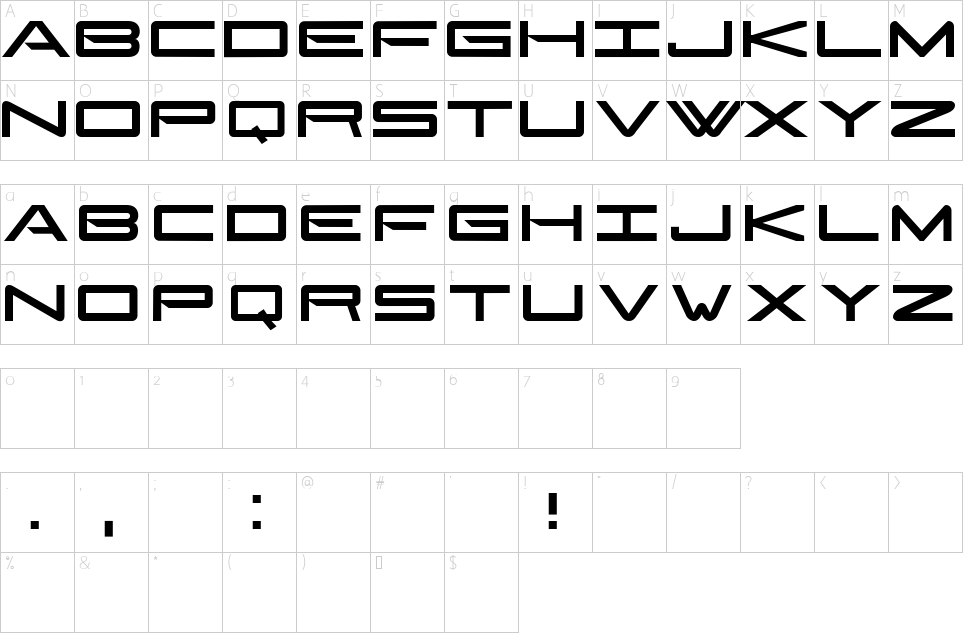
Aqui está uma descrição em português do Brasil para a página de download da font ‘Gonzales Sans Font – 1001 Free Fonts’: Descubra Gonzales Sans, uma elegante e moderna fonte sans-serif disponível gratuitamente para Windows e Mac. Desenhada por Manfred Klein, esta fonte é perfeita para projetos que exijam sofisticação e simplicidade no design. Com um estilo minimalista mas versátil, Gonzales Sans combina perfeitamente com vários estilos de design gráfico, incluindo branding, interfaces de usuário modernas e materiais digitais. Sujeite-se ao bom olhar da comunidade de designers que já usaram esta fonte em suas criações. Se você está procurando por uma opção prática para personalizar seu website ou aplicativo sem precisar gastar nada extra na sua conta, Gonzales Sans é a escolha ideal. Garanta seu próprio arquivo e comece a usar essa fonte imediatamente.